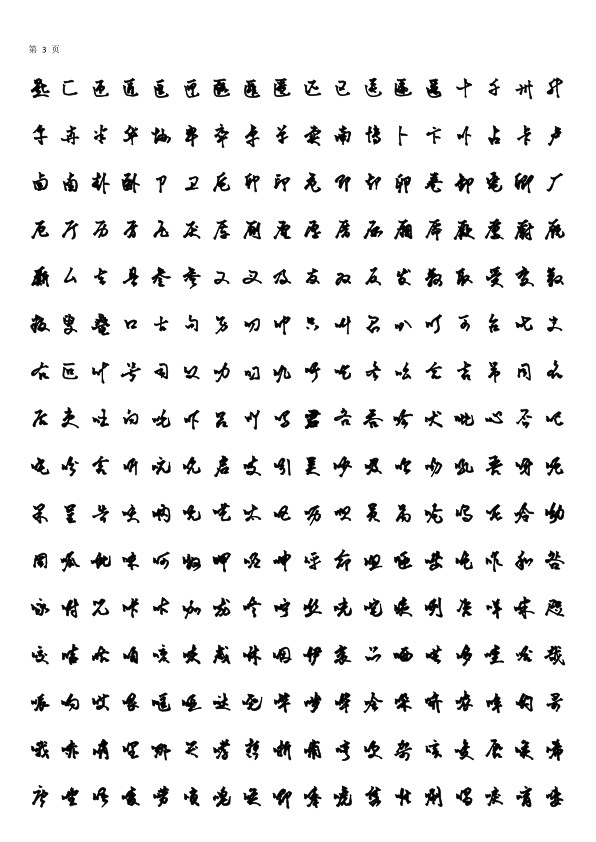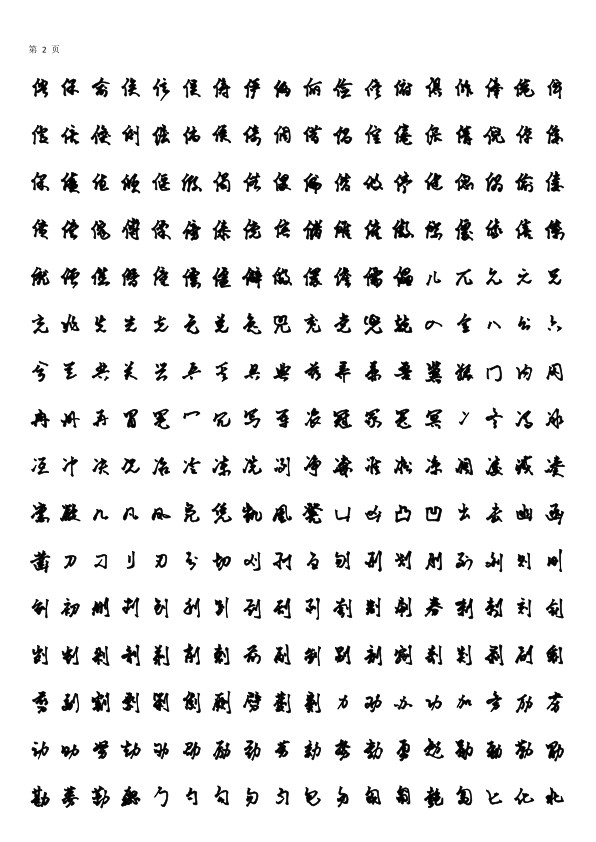
安景臣行草书体(anjingchenxingcaoshuti)
飞流直下三千尺,疑是银河落九天。
风格:草书
类型:草书
描述:安景臣行草书体是安景臣唯一一款草书风格的字体字库。行书字体虽然美观实用,但书写速度不如草书。此字体便是综合了行书和草书的优点而制作的行草书字体。可用于签名设计、书法练字、字帖出版、包装宣传、影视字幕等。有怀素的豪放洒脱与王羲之的热情奔放。强烈推荐!